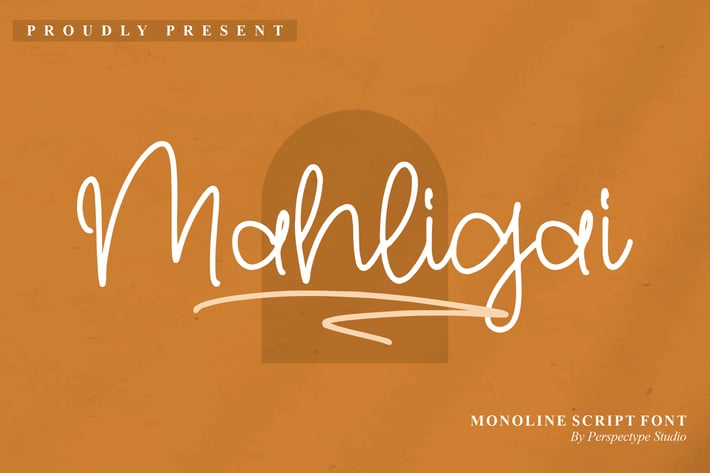
Mahligai Monoline Script Font
Mahligai Monoline Script Font menghadirkan sentuhan sederhana namun berkelas dengan garis tipis monoline yang elegan. Desainnya menghadirkan nuansa kasual namun tetap modern, cocok untuk berbagai kebutuhan branding maupun desain personal. Dengan karakter yang halus dan konsisten, font ini memberikan fleksibilitas untuk menciptakan karya visual yang segar dan stylish.
+ Gaya monoline script yang ringan dan elegan
+ Karakter huruf dengan aliran natural dan rapi
+ Cocok untuk desain kasual maupun profesional
+ Mendukung kebutuhan branding hingga dekoratif
+ Poster & banner promosi
+ Branding produk fashion atau lifestyle
+ Social media posts dengan nuansa elegan
+ Desain undangan atau kartu ucapan
+ Personal project atau logo kreatif
Tambahkan sentuhan modern nan elegan dengan garis monoline yang stylish bersama Mahligai Script!